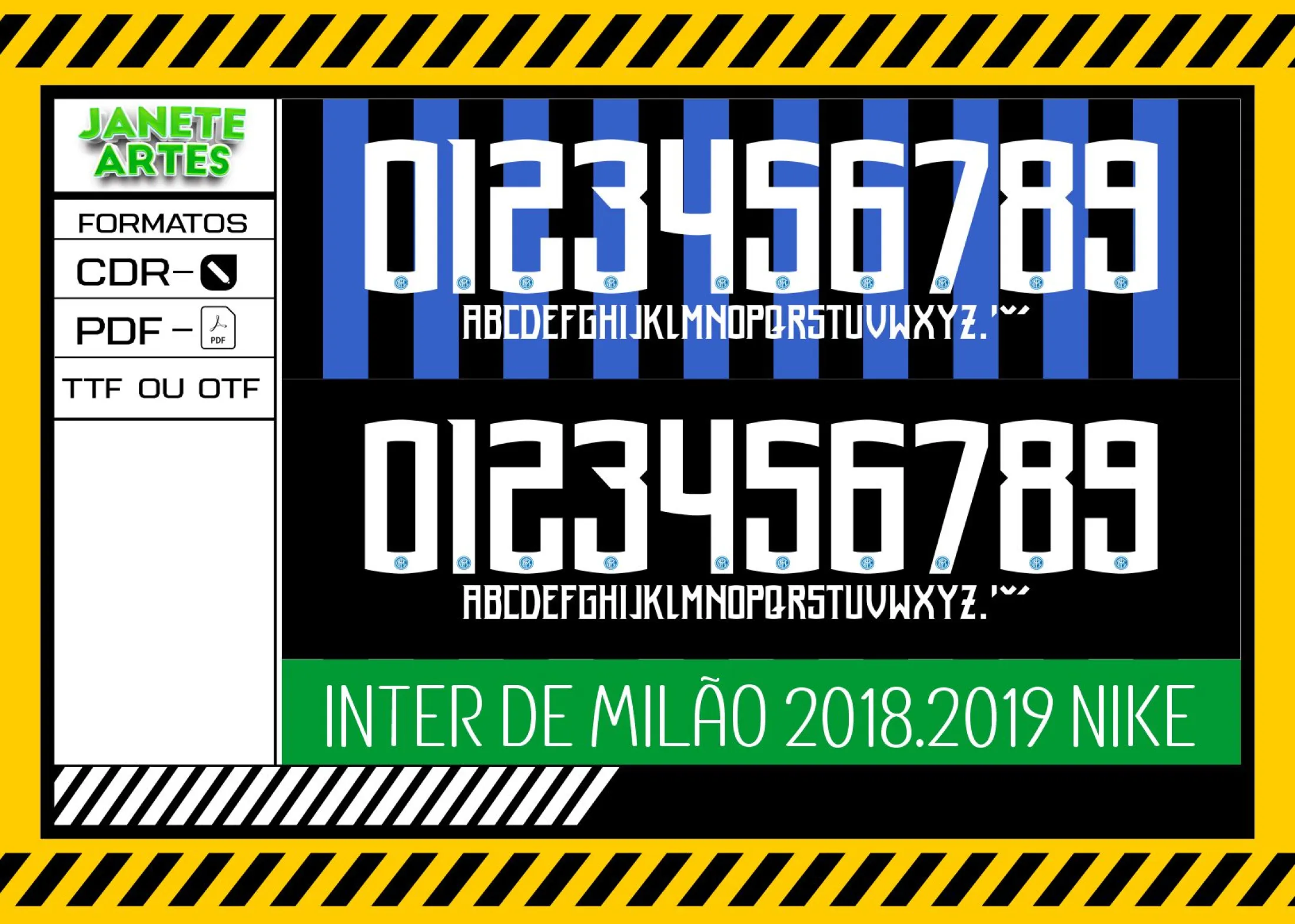
Camiseta unissex preta com logo no peito e estampa grande nas costas baseada na fonte de time tipografia Inter de Milão 2018 2019, estilo moderno e esportivo, perfeita para torcer com estilo.
Fonte de Time Tipografia Inter de Milão 2018 - 2019
Arquivo digital com Fonte de Time Tipografia Inter de Milão 2018 - 2019 para camisetas, ideal para personalizar camisas com estilo único e moderno para torcedores e fãs de futebol.
A inspiração por trás da Arte Camiseta com Fonte de Time Tipografia Inter de Milão 2018 2019
Você já parou para pensar como o design das camisetas pode elevar o espírito do time? Imagine um grupo de amigos; todos apaixonados pelo Inter de Milão, querendo criar suas próprias camisetas para um jogo decisivo. Eles queriam algo exclusivo, que representasse o time com a fonte da camisola entre 2018 e 2019, símbolo de grandes vitórias e emoções. Com esse arquivo, eles conseguiram exatamente isso, personalizando suas camisetas e sentindo a energia de vestir algo que conta uma história. É mais que uma simples impressão, é usar paixão e tradição em cada detalhe.